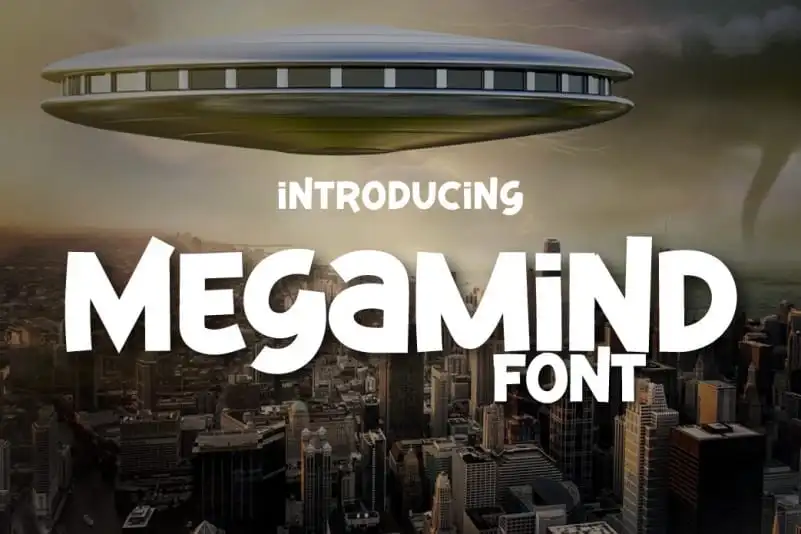
Megamind Display Font – Download Grátis
A Megamind Display Font traz uma nova aparência com um visual elegante e versátil. Esta fonte mantém suas características agressivas, sólidas, claras e poderosas que a tornam perfeita para qualquer projeto de design. Seja para títulos chamativos ou textos detalhados, ela pode se adaptar perfeitamente às necessidades do seu trabalho. O designer twinletter criou uma fonte que não apenas complementa os estilos atuais, mas também adiciona um toque único e moderno a qualquer projeto gráfico. Ideal para anúncios de moda ou designs de aplicativos, essa fonte é uma escolha segura para quem busca expressar seu design com estilo em ambientes digitais contemporâneos.